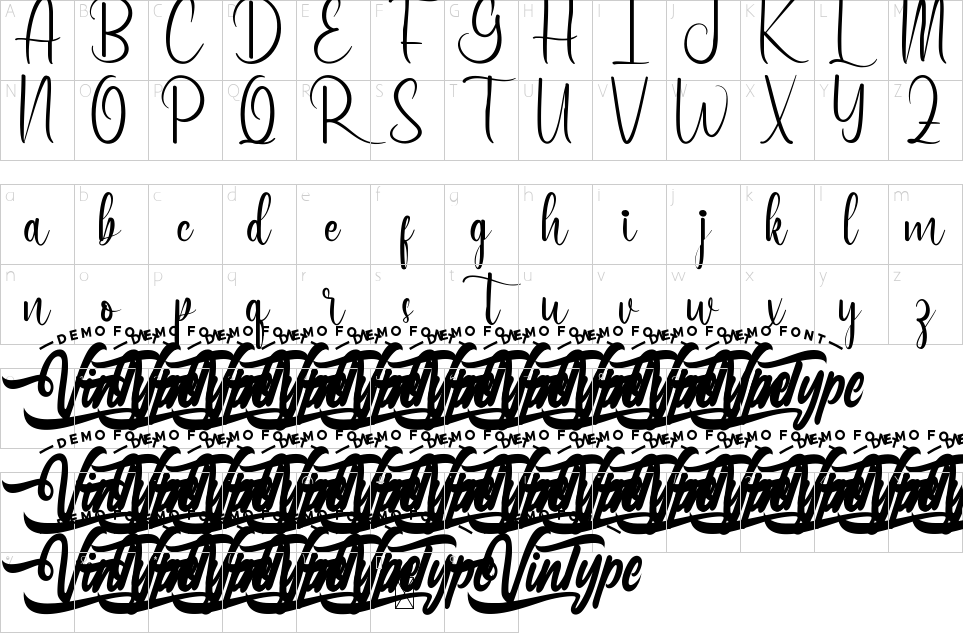
Always There Font
A fonte ‘Always There’ é uma escolha perfeita para qualquer projeto em busca de simplicidade e elegância. Desenvolvida por vintype, esta fonte é uma ótima opção para quem procura uma fonte acessível e prática para uso tanto em dispositivos Windows quanto Mac. Com um design minimalista e suave, a ‘Always There’ é perfeita para aplicações que requerem uma grande estabilidade visual, sem perder a essência gráfica. Com seu design equilibrado e agradável aos olhos, a ‘Always There’ é uma fonte perfeita para criações que valorizam a clareza e a legibilidade. Com um design limpo e sem sobrecarga, esta fonte é uma excelente opção para projetos de design gráfico, websites ou aplicativos que buscam um equilíbrio entre estética e funcionalidade. A fonte ‘Always There’ foi baixada 1.713 vezes e continua a ser uma fonte popular entre designers que procuram uma opção rápida e confiável para seus trabalhos.
Mapa de caracteres da fonte Always There Font